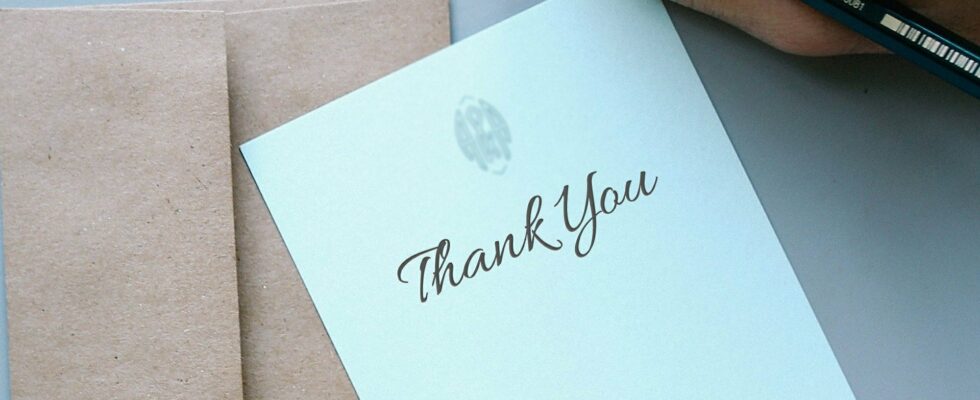
Es gibt etliche Anlässe, die im Nachgang eine Danksagung nach sich ziehen. Da dies meist schriftlich passiert – weil das nun mal mehr hermacht und in großer Stückzahl möglich ist –, muss sich also nach einer Hochzeit, Beerdigung oder Jugendweihe noch für die Gestaltung einer Danksagungskarte entschieden werden.
Das klingt im ersten Moment recht einfach, muss doch nur irgendwo das Wort Danke vorkommen. Steht man dann allerdings vor der Entscheidung, welche Schriftart, Farbe und Form gewählt werden soll, sieht es wieder ganz anders aus. Manche Menschen verrennen sich so lange in die Suche nach der perfekten Karte, dass ihnen am Ende sogar die Zeit knapp wird.
Stilvolle Danksagungen
Auch wenn es zum Glück keinen Trauerfall gab, kann es sein, das Stil über Kreativität gestellt werden muss. Das ist zum Beispiel bei Danksagungen für die Unterstützung während einer Krankheit der Fall. Optima oder Gabrielle sind eine sichere Wahl.
Etwas schicker – aber weiterhin stilvoll – sollten Danksagungen für eine Hochzeit sein. Hierbei handelt es sich um einen schöneren Anlass und das sollten die Danksagungen auch widerspiegeln. Zapfino, Darleston und Heart Romance werden gerne gewählt und mit blumigen Karten oder auch mit einem Foto von der Hochzeit kombiniert.
Freudige Danksagungen
Der Kreativität sind kaum Grenzen gesetzt, wenn es um freudige Anlässe geht. Die Geburt eines Babys, ein Kindergeburtstag oder auch die Einschulung – das sind Momente, in denen Danksagungen ruhig etwas ausgefallener werden dürfen. Garden Gnome und Happy Kids sind tolle Schriftarten, die etwas fetziger wirken.
Je älter die Kinder sind, umso mehr können sie auch in die Gestaltung miteinbezogen werden. Oftmals haben sie tolle Ideen, die nur etwas überwacht werden müssen. Ein Handabdruck in Fingermalfarbe kann der Danksagung zum Beispiel das gewisse Etwas geben.
Aber natürlich dürfen sich nicht nur Kinder ein wenig austoben, wenn die Danksagung einen so freudigen Anlass hat. Auch im Erwachsenenalter kann man sich beispielsweise für eine tolle Geburtstagsfeier bedanken. War es ein ruhiger Abend in einem Restaurant, sind die vorher genannten stilvollen Schriften gut geeignet. Gab es hingegen eine feuchtfröhliche Party mit viel Musik und verrückten Erlebnissen, dann darf die Danksagung das auch ruhig zeigen.
Festliche und weitere Danksagungen
Richtig spaßig ist die Gestaltung von Danksagungen, die ein festliches Event als Grundlage haben. Oster- und Weihnachtsfeiern sind hier an erster Stelle zu nennen. Denn dann kann die Danksagung logischerweise im weihnachtlichen Stil gestaltet werden (Tannenbäume, Rot-Grün-Design) oder aber mit Ostereiern und Häschen.
Es gibt auch Danksagungen, die nicht in Form einer Karte gestaltet werden. Hilft jemand bei dem Verfassen eines Romans oder Sachbuchs, dann sollte dies im Werk erwähnt werden. Möglicherweise kann auch eine mündliche Danksagung angebracht sein, zum Beispiel wenn jemand bei der Hilfe einer Veranstaltung geholfen hat – sollte sich die Chance ergeben, eine Rede zu halten, sollten die wichtigsten Personen erwähnt werden.
Mittlerweile werden Danksagungen auch nicht mehr nur als klassische Karte verschickt. Auch Online-Danksagungen sind üblich. Für Hochzeiten gibt es sogar den Trend, kleine Videos als Danksagung zu verschicken, die Aufnahmen von der Hochzeit zeigen. Auch hier sollte ein gewisser Stil gewahrt werden – was unter anderem durch die passende Schriftart geschehen kann.